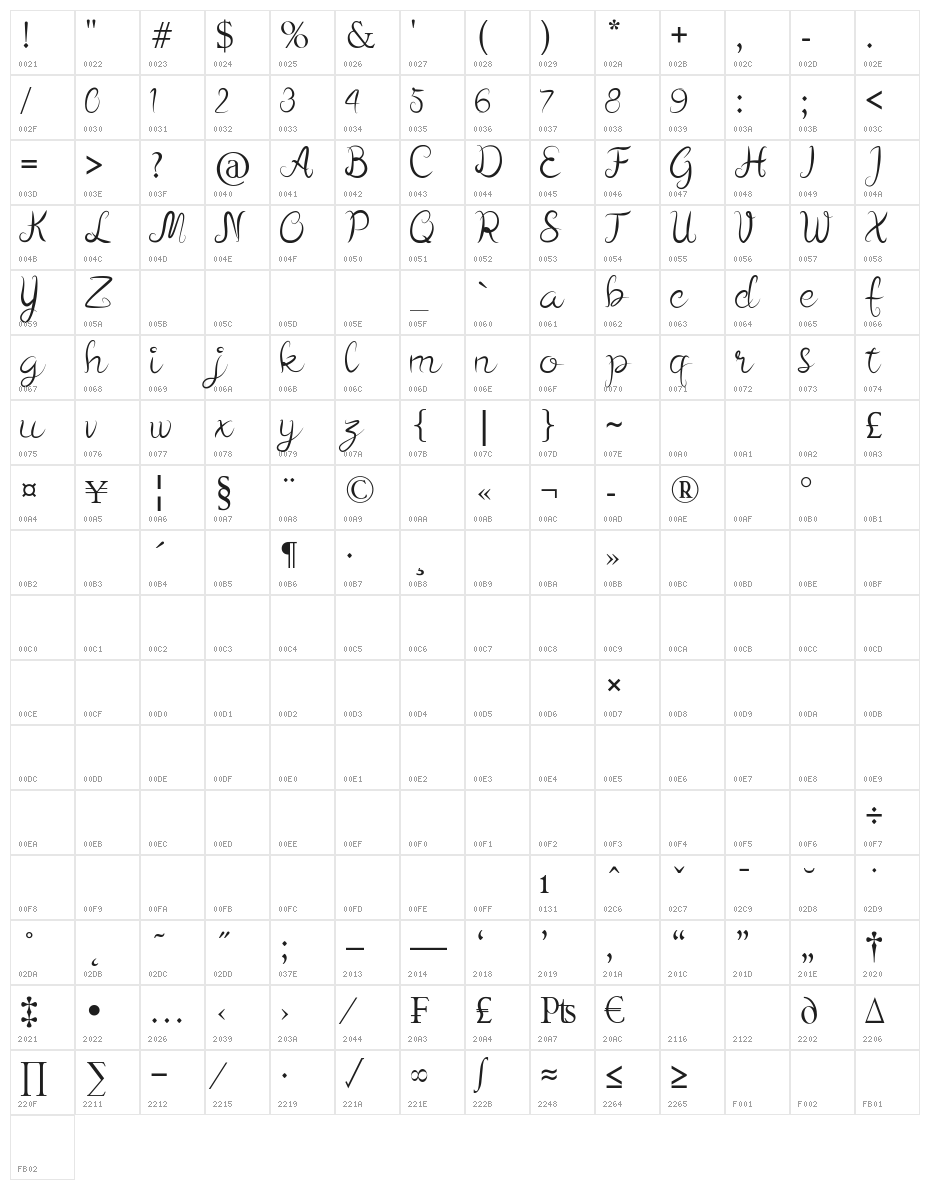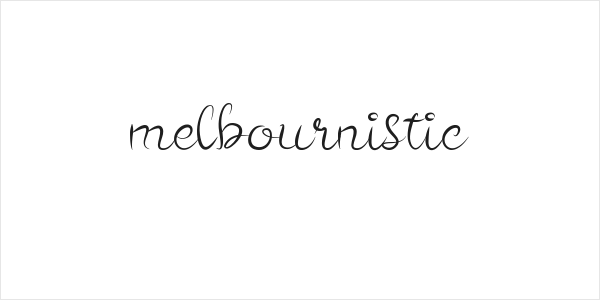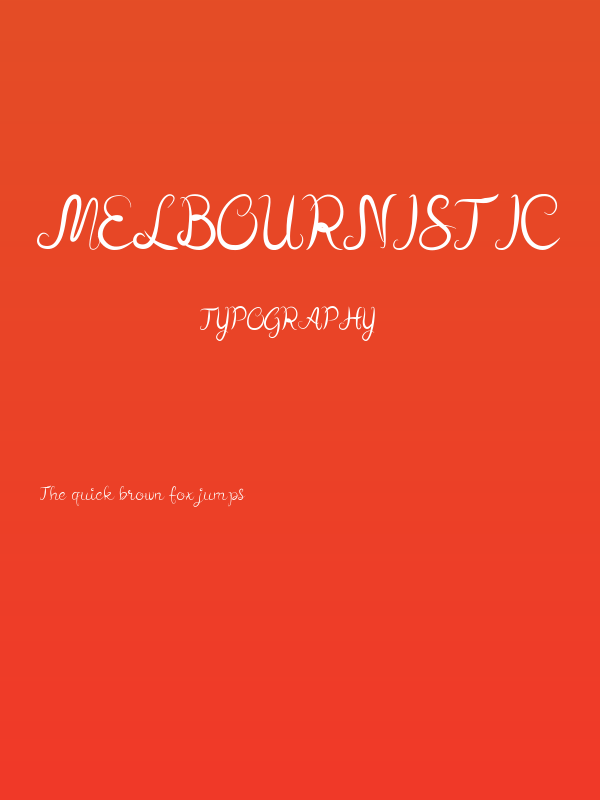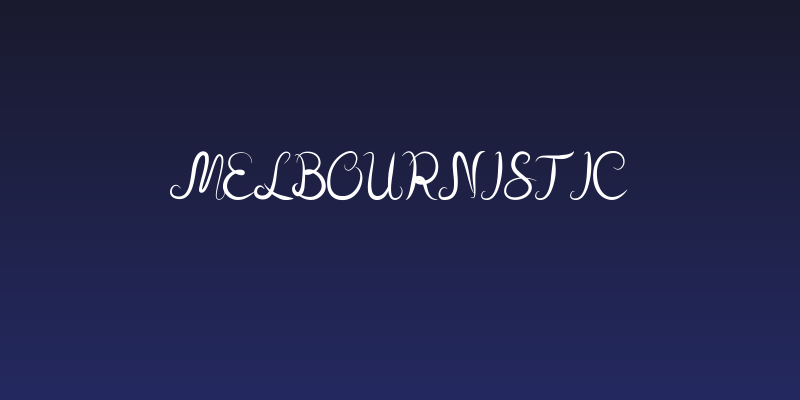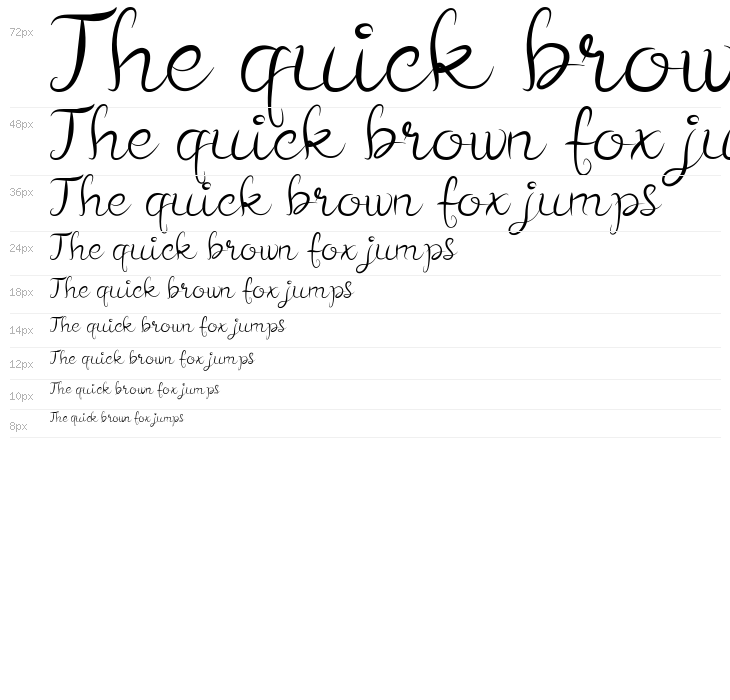
melbournistic Font
| Stile generale | Elegant |
| Caso d'uso | Logos, Invitations, Branding |
| Progetti proposti | Ideal for wedding invitations, elegant branding, luxury packaging, and sophisticated editorial design. |